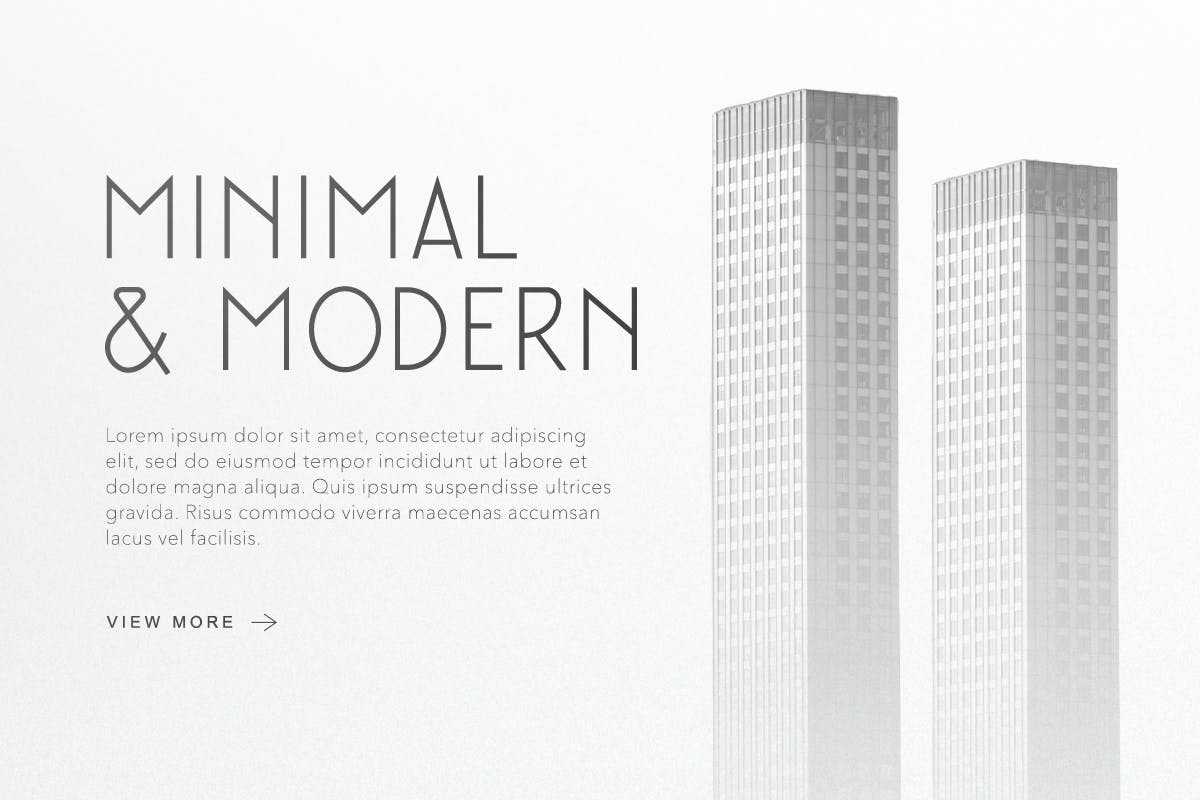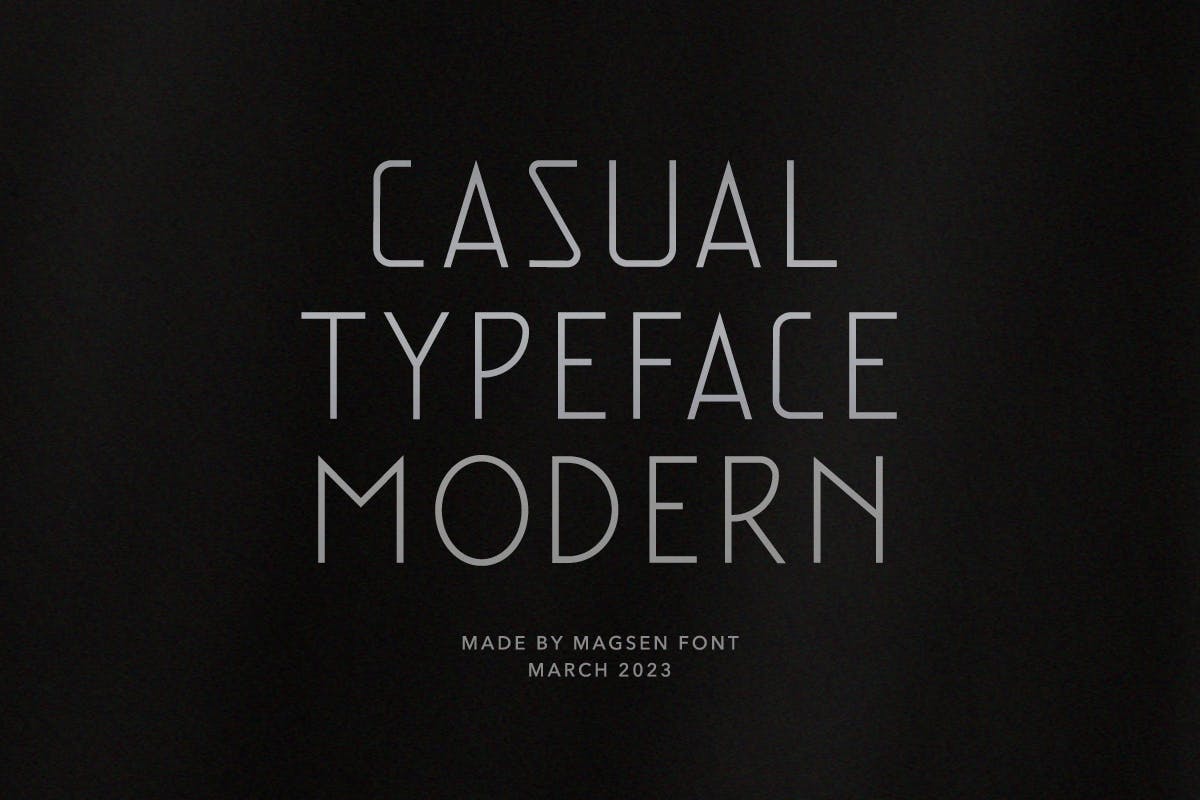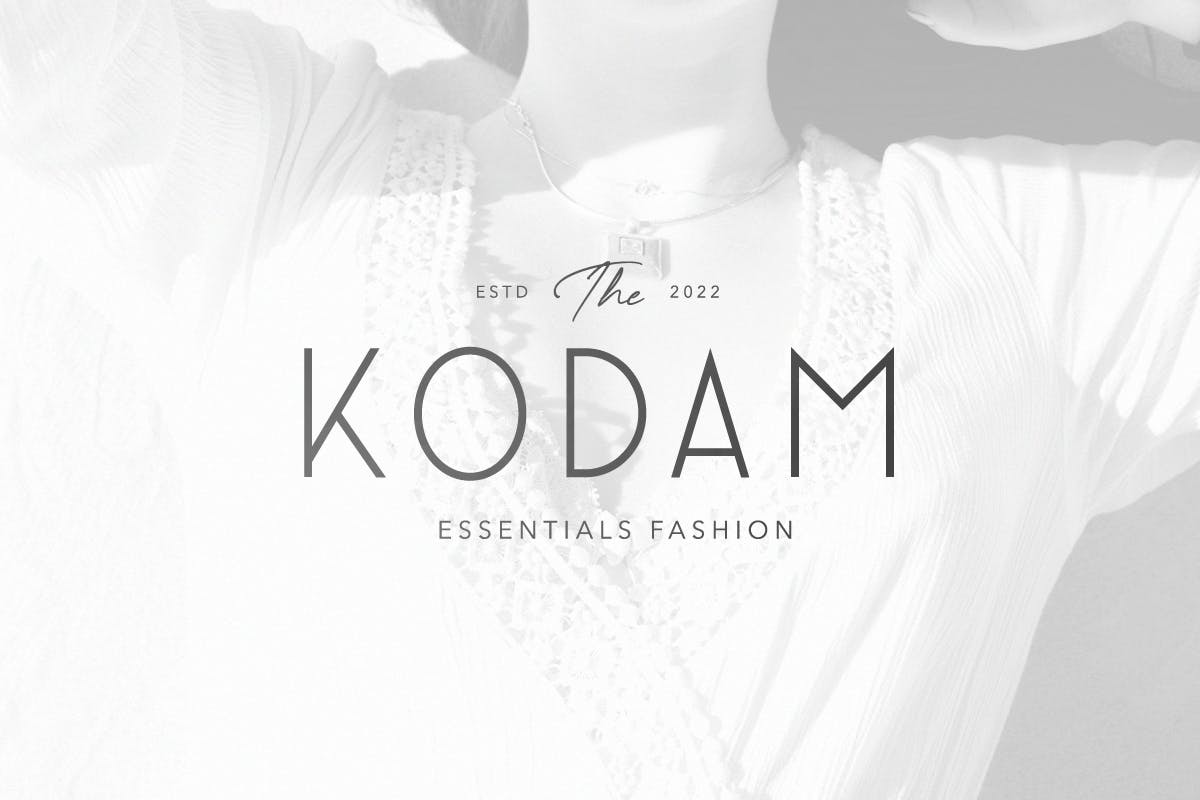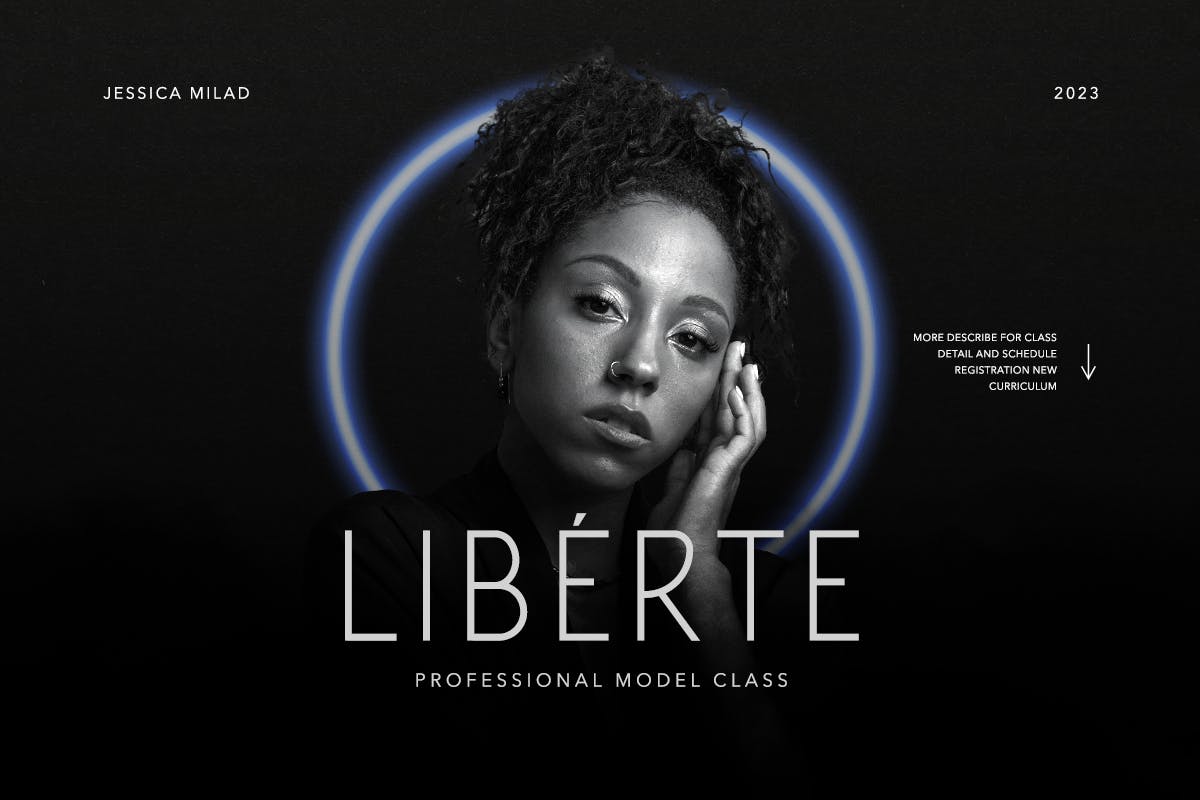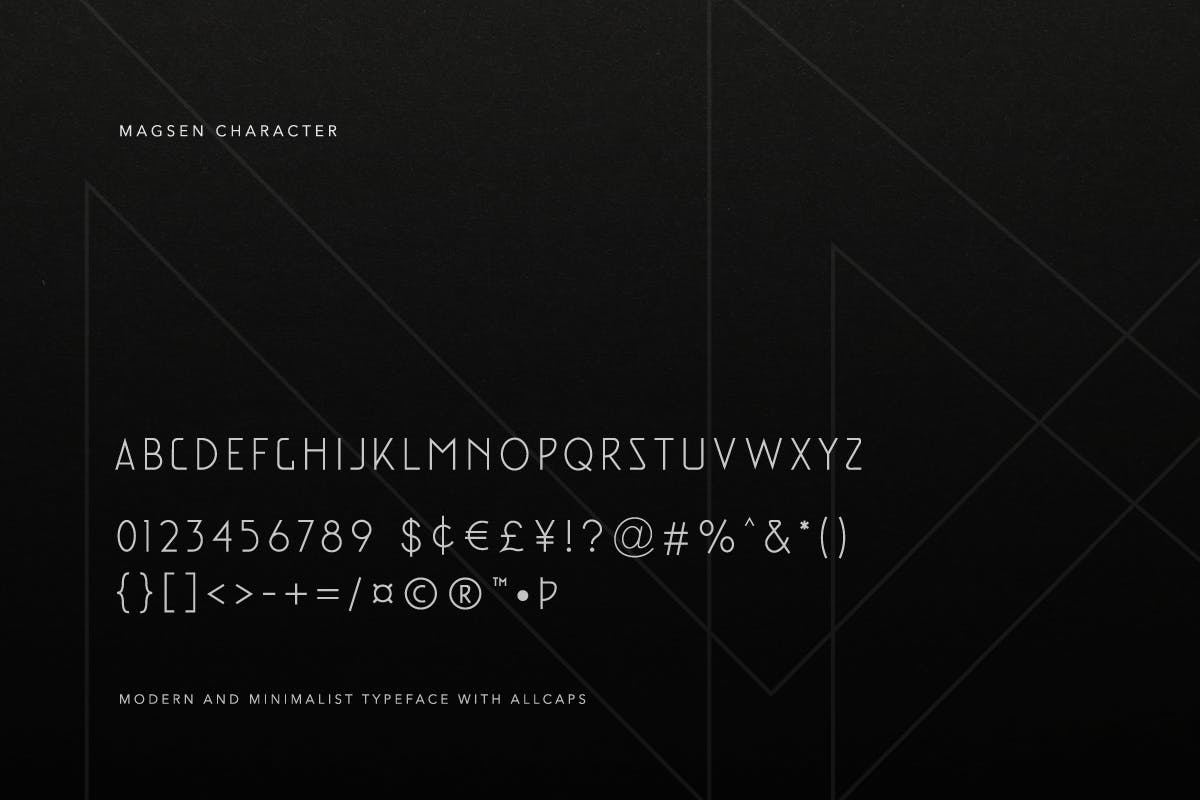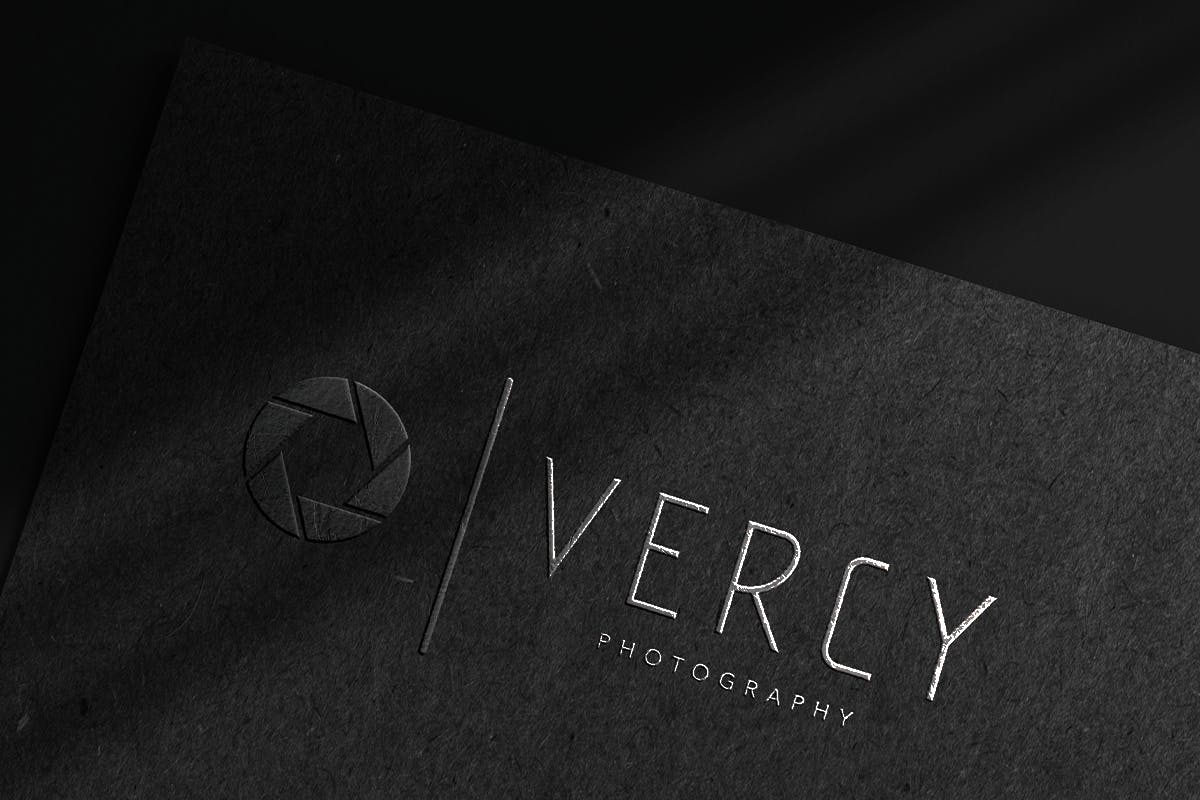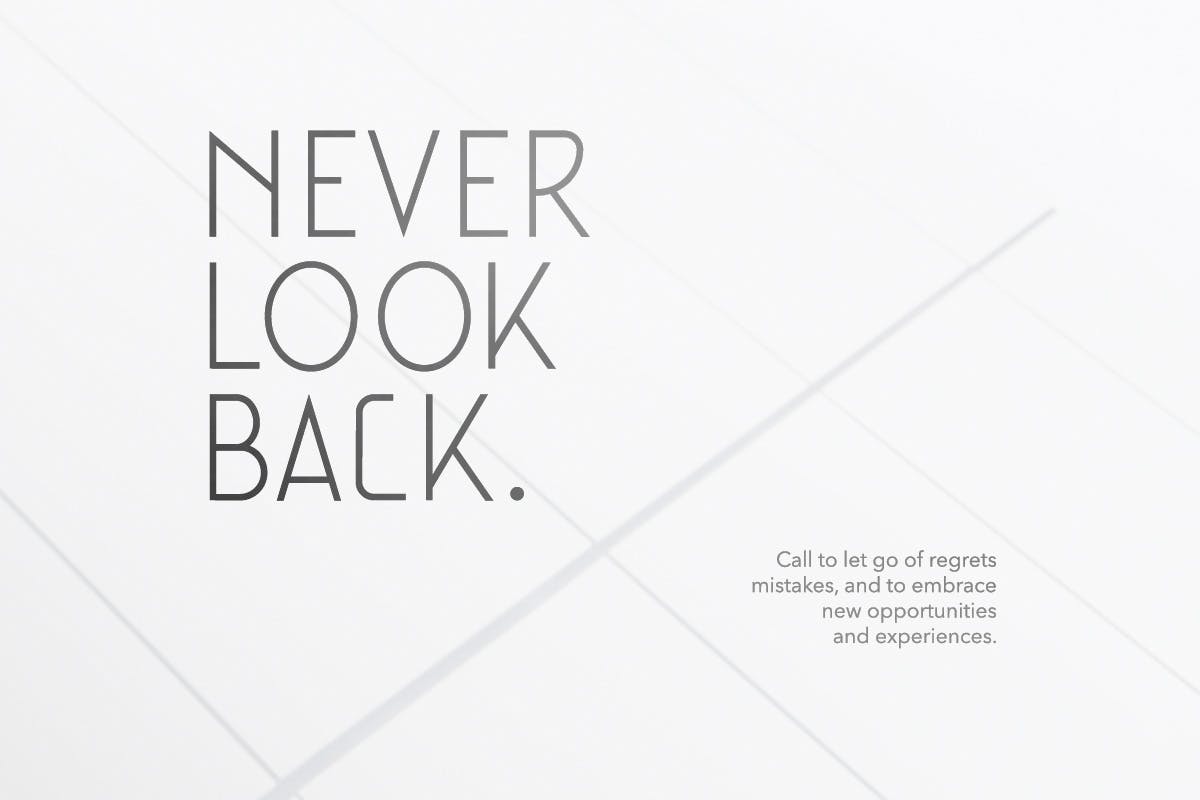
فونت Magsen یک فونت مدرن بدون سریف است که ترکیبی بینظیر از ظرافت، مینیمالیسم و حس نیمهتکنولوژیک را ارائه میدهد. این فونت با تمرکز بر سادگی، خطوط تمیز و زیباییشناسی معاصر طراحی شده است و انتخابی ایدهآل برای طراحانی است که به دنبال ظاهری مدرن و مینیمالیستی هستند.